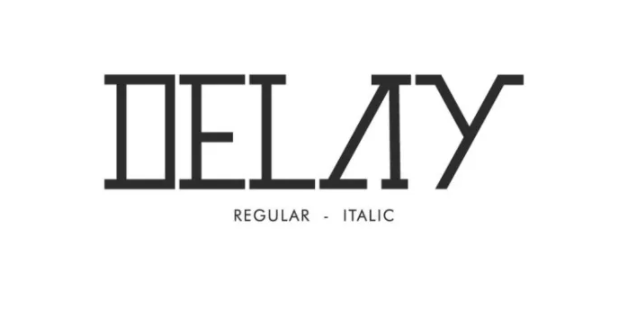
[Fontbundles] Delay Font (2021)
Шрифт Delay - это семейство шрифтов с засечками и двумя различными стилями:
Шрифт Delay отлично подойдет для любых проектов, включая: брендинг, логотип, канцелярские товары, визитные карточки, вывески, флаера, брошюры и т.д.